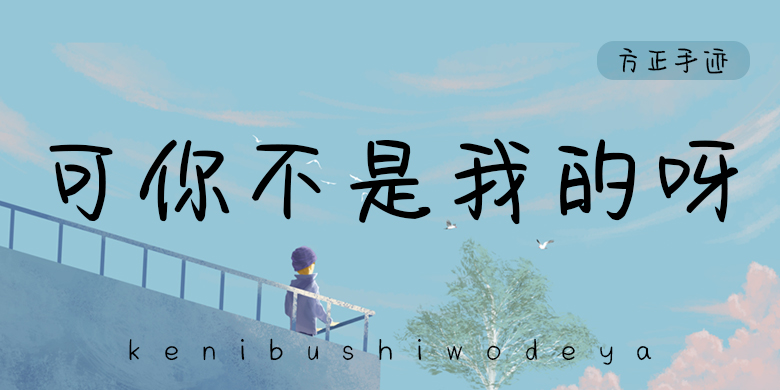
方正手迹-可你不是我的呀
方正手迹-可你不是我的呀,这款字体结构工整、笔画清晰,兼顾美观与易读性,适用于标题、正文、海报、包装、LOGO 等多种场景。字形优雅稳定,风格百搭耐看,适配日常排版与创意设计,让文字呈现更舒适、更具质感。方正手迹-可你不是我的呀一笔一画,皆是细节,以均衡的比例、流畅的线条打造舒适视觉体验,字形端正大气,风格简约现代。无论是商业设计、品牌宣传还是日常排版,都能轻松驾驭,让文字更有格调与力量。方正手迹-可你不是我的呀字体下载。
字体品牌: 方正手迹 设计师:余丹 字体分类:创意书写 字体属性:精品字 字符集:简繁扩展(GBK) 发布时间: 2020
可你不是我呀是一款可爱风格的手写体,整体字形偏扁,笔画多取曲势,温暖可爱而又趣味生动,适用于儿童类文艺类品牌广告和产品包装设计,以及社交网络的个性化用字。